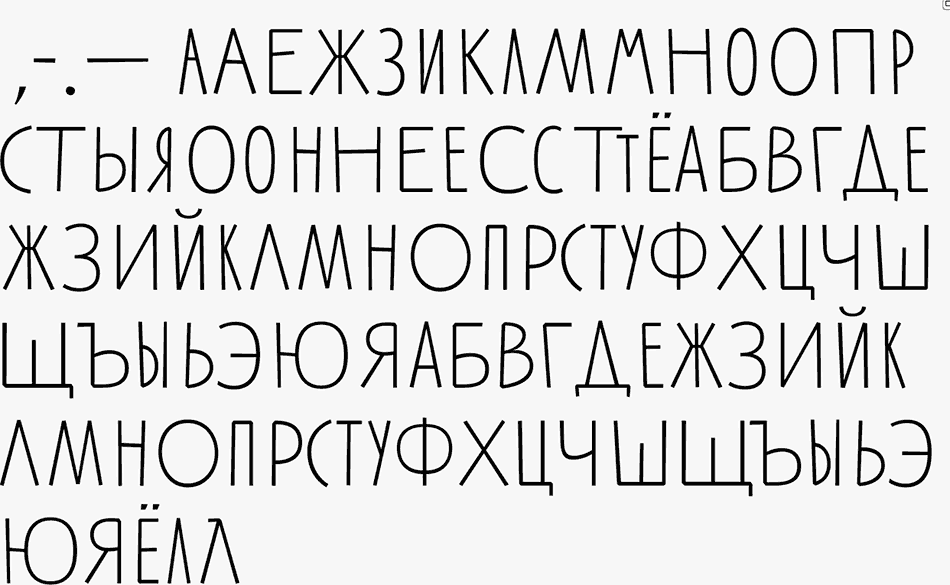
Куцын Т. И. Начертание шрифтов : Пособие для архитекторов и инженеров. — М., 1950
Начертание шрифтов : Пособие для архитекторов и инженеров / Т. И. Куцын. — Москва : Государственное издательство архитектуры и градостроительства, 1950. — 204 с., ил.
ВВЕДЕНИЕ
Современные буквы являются результатом долгих эволюций алфавита, повидимому, от египетских иероглифов, через финикийский до греческого алфавита. Из этих форм раннего письма развились обе главные разновидности шрифта — славянский (в IX в.) и латинский (в V в.).
Древнейшие памятники славянской письменности написаны двумя отличными друг от друга алфавитами, известными под названием «кириллицы» и «глаголицы». Оба этих славянских алфавита выработались почти одновременно, причем в основу «кириллицы» легло письмо, составленное из заглавных букв, а «глаголицы» — из строчных букв. В начале XI века «кириллица» стала заменять «глаголицу».
Общим для обоих алфавитов является одинаковый порядок букв, а разнятся они в начертаниях и численных значениях букв.
До этого времени известны три способа письма: устав, употреблявшийся до XIV века, полуустав, существовавший до XVII века, и скоропись, которая постепенно, начиная с XVI века, начала заменять полуустав. Дошедшие до нас русские чертежи XVII века были надписаны скорописью.
Петр I ввел упрощенную азбуку и назвал ее гражданской. 1 марта 1708 года вышла первая книга, напечатанная гражданским шрифтом, который в его рафинированном виде (академический, елизаветинский, пальмира и др.) широко применяется и теперь. Этот гражданский шрифт, утвержденный Петром I в 1710 году, является одним из самых классических примеров оригинального русского шрифта. Наличие в этом шрифте национальных особенностей несомненно. Гражданский шрифт оставался без существенных изменений до 1740 года. В дальнейшем он был видоизменен в петербургской типографии Академии, наук и приобрел новые самобытные черты.
В XVIII и в начале XIX века чертежи надписывались от руки существовавшими тогда почерками — специальных чертежных шрифтов еще не существовало. Впервые они появились в 40-х годах XIX века. Это были художественные шрифты — славянский, рондо, курсив и готический, определявшие лишь начертания букв, но не их наклон и размер. Только в середине 70-х годов прошлого столетия этот специальный шрифт, круглый или рондо, начал определять размеры и наклон букв. Этим шрифтом можно быстро исполнять довольно красивые надписи. Но шрифт рондо имеет существенные недостатки: мелкие надписи выходят грубовато и занимают много места; при размножении светокопированием тонкие отдельные элементы букв плохо отпечатываются на синьке.
Значительное место в оформлении чертежей занимают рамки. До XVIII века рамки для чертежей применялись в России как исключение, и только в 40-х годах того же века стали применяться главным образом прямые рамки, часто в виде широкой полосы, начинающейся сразу с края бумаги.
До второй половины XVIII века характерны художественные рамки, расписанные золотом и виньетками, с закругленными углами и т. д. К началу XIX века такие рамки постепенно заменялись простыми, сохранившись главным образом в проектах, подаваемых на «высочайшее утверждение». Но, начиная с 70-х годов прошлого столетия, даже простые рамки постепенно выходят из употребления¹.
После Великой Октябрьской социалистической революции, когда широко развернулось строительство, оформлению чертежей начали придавать все большее и большее значение. В 30-х годах нашего века большое распространение в исполнении надписей в чертежах получил нормальный шрифт. В 1932 году на этот шрифт, как рекомендуемый, был установлен ОСТ 353, а с 1946 года этот шрифт уже является обязательным согласно ГОСТ 3454—46.
Трудами целого ряда советских художников в области начертания шрифтов достигнуты за последние годы значительные успехи.
Из советских художников, много сделавших в области разработки новых типов шрифтов, можно назвать следующие имена: И.
Особо надо выделить работы заслуженного деятеля науки и техники проф. Д. И. Каргина; им разработан и удостоен премии на международном конкурсе шрифт антиква «эмке». Шрифт этот предназначен для художественной печати; им печатаются книги в СССР. Позже проф. Д. И. Каргиным была выполнена крупная работа², в которой им были предложены и обоснованы изменения стандартного шрифта.
_________
¹ Подробно см. диссертацию А. А. Кузина «Очерки по истории технических документальных материалов в дореволюционной России» в Историко-архивном институте.
² Доложена на научно-технической конференции ЛИИЖТ в 1941 году.
СОДЕРЖАНИЕ
Предисловие. 3
Введение 5
Глава I. Общие положения… 7
Глава II. Основы шрифтовой графики… 8
Глава III. Нормальный шрифт..11
Глава IV. Шрифт зодчего 16
Глава V.
Романский шрифт .. 21
Глава VI. Различные виды чертежных шрифтов 23
Глава VII. Расстановка букв в словах…25
Глава VIII. Исполнение заголовков и их композиция 34
Глава IX. Штампы и рамки на чертежах . 37
Глава X. Чертежные инструменты и материалы 38
Глава XI. Практика…40
Глава XII. Типичные ошибки..44
Контрольные вопросы по шрифтам…45
Таблицы..47
Перечень таблиц..201
Литература…203